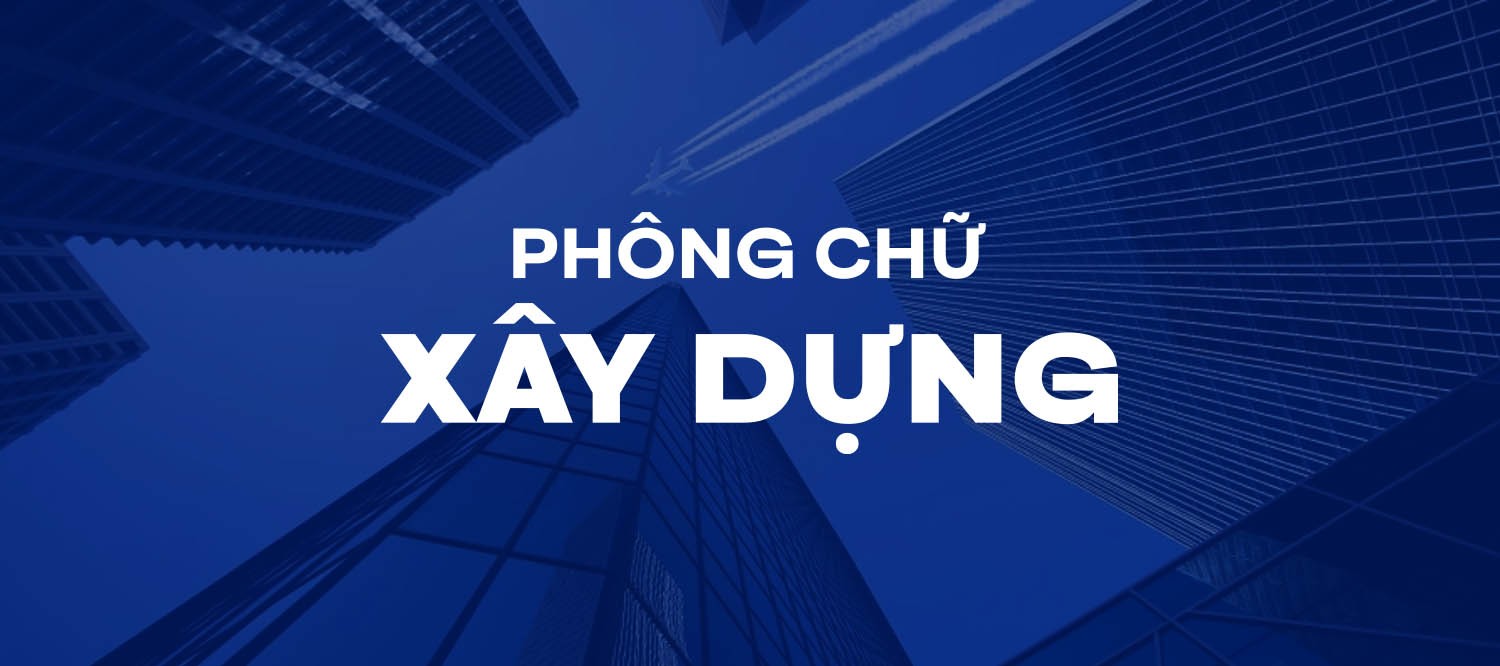
Font chữ là một phần quan trọng trong việc xây dựng hình ảnh thương hiệu của các công ty trong ngành kiến trúc. Một font chữ cứng cáp không chỉ giúp dễ dàng nhận diện mà còn thể hiện được sự mạnh mẽ, chuyên nghiệp của doanh nghiệp. Trong ngành kiến trúc, nơi yêu cầu tính rõ ràng và chắc chắn, việc lựa chọn font chữ phù hợp là điều không thể thiếu.
Đặc điểm của một font chữ cứng cáp bao gồm độ đậm, đường nét rõ ràng, dễ đọc từ xa và dễ nhận diện trong mọi môi trường, đặc biệt là trong các dự án công trình. Các font chữ mạnh mẽ này còn giúp tạo dựng sự uy tín và khẳng định vị thế của doanh nghiệp trong mắt khách hàng.
Barlow là font chữ sans-serif với thiết kế cứng cáp, thích hợp cho ngành kiến trúc và các dự án kỹ thuật. Đặc trưng của Barlow là các đường nét rõ ràng và mạnh mẽ, mang lại sự chuyên nghiệp và dễ đọc trong mọi điều kiện ánh sáng.
Barlow là lựa chọn hoàn hảo cho các biển hiệu công trình, logo công ty kiến trúc, và các tài liệu quảng cáo.
SVN Gilroy là một font chữ sans-serif hiện đại, thiết kế để mang lại sự nổi bật và dễ dàng nhận diện, rất phù hợp cho các công ty kiến trúc muốn tạo dựng hình ảnh chuyên nghiệp và mạnh mẽ.
Font này thích hợp cho các dự án quảng cáo, biển hiệu và tài liệu kỹ thuật.
Font chữ TH Cungcap 12 được thiết kế với độ mạnh mẽ và dứt khoát, lý tưởng cho các biển hiệu, logo của ngành kiến trúc. Đường nét đơn giản nhưng vẫn thể hiện sự uy tín và cứng cáp.
Thích hợp cho các công ty kiến trúc lớn và các biển hiệu công trình.
Wolgen là font chữ với phong cách công nghệ hiện đại, rất phù hợp cho các công ty kiến trúc đang hướng đến sự đổi mới và áp dụng công nghệ vào các dự án của mình.
Font này phù hợp cho các công ty kiến trúc trong ngành công nghệ cao, thiết kế các công trình thông minh.
Font chữ TH Cungcap 7 có phong cách thiết kế mạnh mẽ, rõ ràng và dễ đọc, phù hợp cho các công ty kiến trúc khi tạo dựng thương hiệu hay thiết kế biển hiệu công trình.
Dùng trong logo công ty, biển hiệu công trình và các tài liệu xây dựng.
Font chữ TH Cungcap 5 mang đến cảm giác mạnh mẽ và cứng cáp, rất thích hợp cho các công ty kiến trúc quân sự hoặc các công ty yêu cầu sự mạnh mẽ trong thiết kế.
Sử dụng trong các dự án xây dựng, kiến trúc liên quan đến quốc phòng và các công ty quân đội.
Futurama mang đến một phong cách hiện đại, trẻ trung, dễ dàng ứng dụng cho các dự án kiến trúc liên quan đến công nghệ cao và các công trình có tính sáng tạo.
Phù hợp cho các công ty xây dựng hiện đại và các dự án sáng tạo.
Font Striger mang đến một cảm giác mạnh mẽ và thể thao, rất phù hợp cho các dự án kiến trúc có yếu tố trò chơi hoặc thể thao. Font này dễ đọc và rõ ràng, mang lại sự chắc chắn trong thiết kế.
Dùng cho các dự án kiến trúc công trình thể thao, game hoặc công nghệ.
Teroxia Pro là font chữ hiện đại với phong cách thiết kế sắc nét, rất phù hợp cho các công ty kiến trúc muốn thể hiện sự chuyên nghiệp và đổi mới trong các thiết kế quảng cáo và biển hiệu.
Thích hợp cho các biển hiệu công trình, tài liệu quảng cáo.
Neo Cybern là font chữ mạnh mẽ, hiện đại, rất phù hợp cho các dự án kiến trúc có tính công nghệ cao hoặc các công trình đòi hỏi sự chắc chắn và dễ nhận diện.
Dùng trong các công trình kiến trúc hiện đại và các ứng dụng công nghệ.
Enixe là một font chữ có phong cách hiện đại, thích hợp cho các dự án công nghệ, game và kiến trúc. Được thiết kế để tạo dựng ấn tượng mạnh mẽ, font chữ này sẽ mang lại sự chuyên nghiệp cho mọi công trình.
Dùng cho các công ty xây dựng trong ngành công nghệ hoặc game.
Republica Minor là font chữ tròn, mạnh mẽ và cứng cáp, rất phù hợp với các công ty kiến trúc liên quan đến ngành cơ khí hoặc công nghiệp nặng.
Sử dụng trong các công trình cơ khí xây dựng.
Cintra là font chữ hiện đại, mạnh mẽ và dễ đọc, rất phù hợp cho các công trình cơ khí xây dựng và các trò chơi điện tử, game thể thao.
Ứng dụng: Dùng trong các công trình cơ khí xây dựng và các dự án game.
The Mantra Key mang đến sự mạnh mẽ, rõ ràng và phù hợp cho các công ty kiến trúc hoặc các dự án cần sự rõ nét và mạnh mẽ.
Dùng cho các dự án xây dựng yêu cầu tính dễ đọc và chắc chắn.
Font chữ UTM Neutra có phong cách thiết kế thanh thoát nhưng vẫn đảm bảo sự mạnh mẽ, phù hợp với các công ty kiến trúc hiện đại muốn nâng cao hình ảnh thương hiệu.
Dùng cho các biển hiệu và tài liệu quảng cáo của công ty xây dựng.
Việc lựa chọn font chữ phù hợp là một phần không thể thiếu trong việc xây dựng thương hiệu của các công ty xây dựng. Các font chữ mạnh mẽ, dễ đọc và có tính ứng dụng cao sẽ giúp doanh nghiệp dễ dàng nhận diện và tạo ấn tượng với khách hàng. Bài viết đã giới thiệu 15 font chữ cứng cáp Việt hóa, mỗi font đều có những ưu điểm riêng phù hợp với các nhu cầu khác nhau trong ngành xây dựng. Hãy lựa chọn font chữ phù hợp nhất với phong cách và mục đích sử dụng của bạn để nâng cao hình ảnh và chuyên môn của công ty mình.